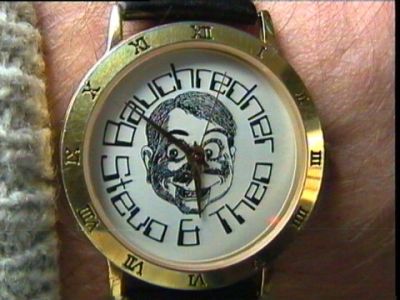
"et" schaut aus wie "6"
Vor Jahren habe ich dieses Ziffernblatt für meine Uhr entworfen, mit einem Einbauprogramm von MS-WORD das WORDART heißt oder hieß.
Einige Computer und Betriebssystemgenerationen später ( = jetzt) kann ich weder die Schrift identifizieren (die muß damals bei WORD vorinstalliert gewesen sein), noch kann ich den Schriftzug bearbeiten, weil ich über WORDART nicht mehr verfüge.
Frage: Welche Schrift ist das? Welche Schriften haben auch ein "et"-Zeichen, das wie eine Ziffer "6" aussieht?
Solche Technofonts gibt es sehr viele, einer der recht nah dran ist, wäre die Data 70.